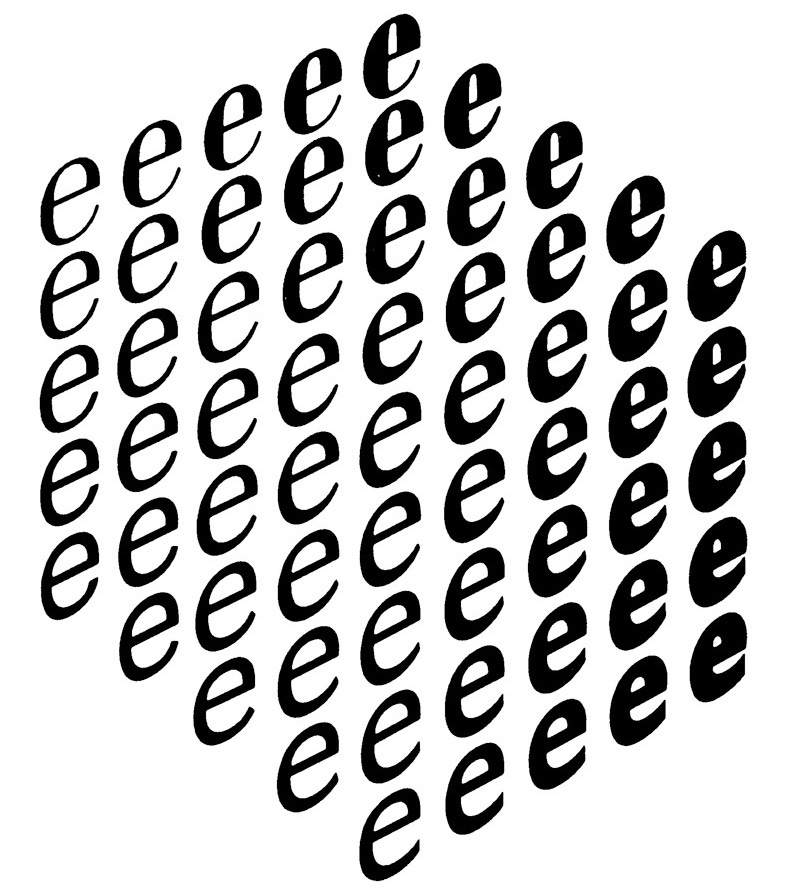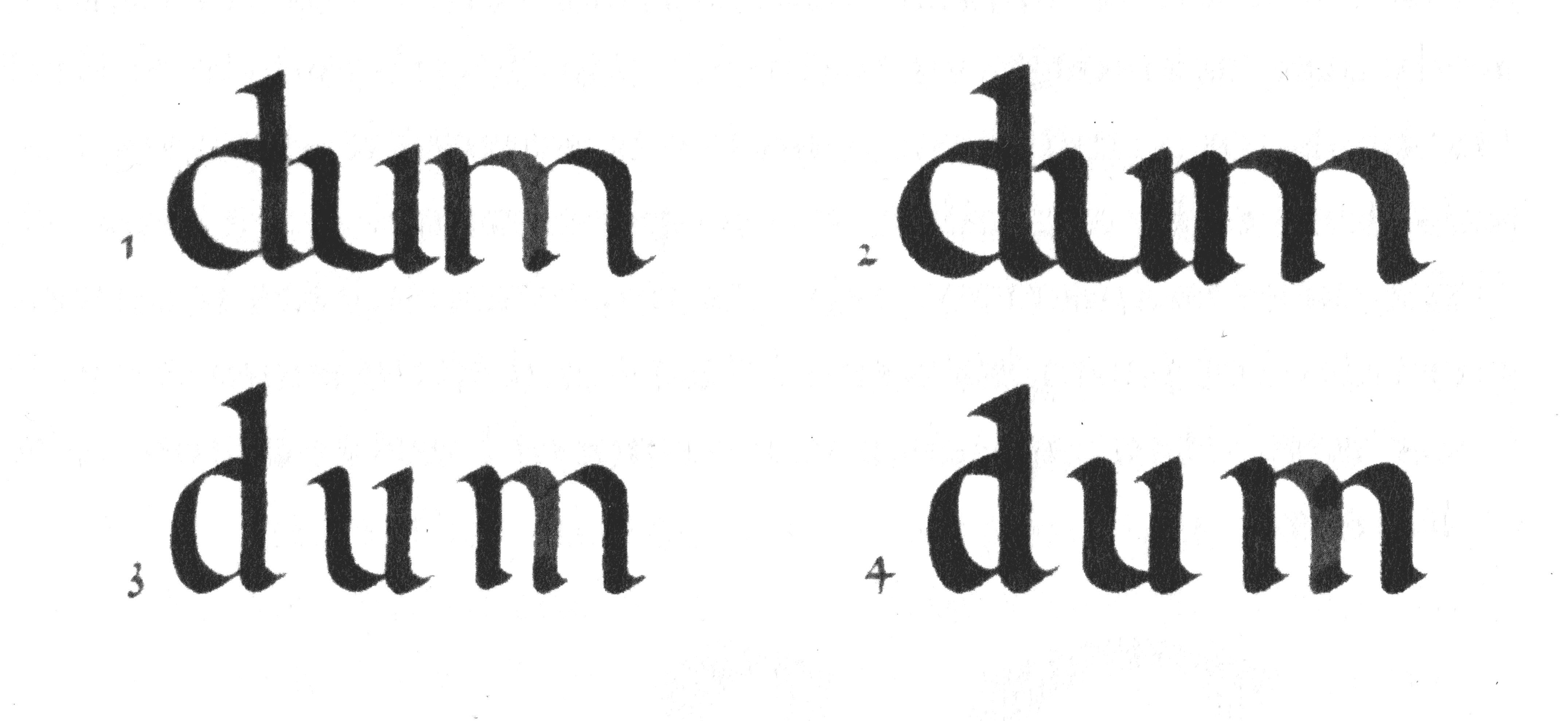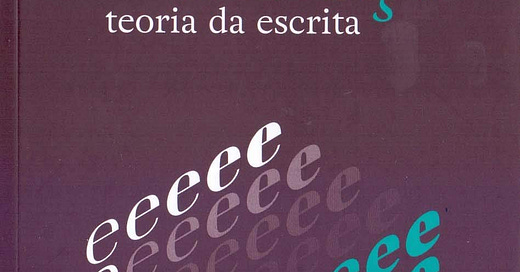
O traço é o artefato fundamental. Nada é mais primordial que a forma de um único traço. Não podemos pressupor uma forma desenhando primeiramente seu contorno, porque qualquer desenho (incluindo os contornos) começa com a forma. Contornos são as bordas das formas. Se uma forma não existir, também não haverá um contorno.
Existe algo encantador no ser humano que desperta quando aprendemos e entendemos algo complexo a partir de seus conceitos mais simples e basilares. Imagine você, quando criança, vendo Carl Sagan explicando a quarta dimensão, um conceito tão intangível e complexo, a partir de um quadrado num plano e uma maçã voadora deixando impressões e fazendo sua silhueta aparecer enquanto ela se move numa dimensão inimaginável para um simples quadrado. Muitas áreas de conhecimento têm a oportunidade de conquistar alguém pelo fascínio de entender as coisas pelas suas fundações, quando temos alguém hábil e generoso o suficiente para explicá-las.
Uma dessas pessoas partiu para as estrelas recentemente: o professor, autor e type designer holandês Gerrit Noordzij. Ao longo de 90 anos vividos em função das letras, Gerrit deixou centenas de alunos, uma vasta contribuição para o ensino de tipografia e design de tipos, e um dos livros mais traiçoeiros que alguém pode (se você vive de tipografia, deve) ter na estante. “Traiçoeiro” num bom sentido, antes que pareça uma crítica vazia: ele é bem curto, tem menos de 100 páginas, mas não quer dizer que seja fácil ou de rápida digestão. No entanto, a compreensão sobre tudo que envolve o ato de desenhar letras nunca mais é a mesma depois de tê-lo lido. Espero que você não tenha pensado mal de mim sobre dizer que o livro é “traiçoeiro”: essa edição de hoje não é uma resenha, crítica ou uma análise formal, é só um compilado de divagações para falar bem de O Traço: teoria da escrita (lançado no Brasil pela Editora Blucher), de como os ensinamentos dele são importantes pra mim e pra qualquer um que viva de criar ou trabalhar com letras.
Os estudos contemporâneos sobre a escrita não observam atentamente o branco da palavra, mas o preto da letras. Consequentemente, as considerações se exaurem na exploração de diferenças superficiais. O ponto de vista universal, que permite a comparação entre a escrita manual e a tipografia, não observa o preto da letra. O preto de uma letra tipográfica é tão diferente do preto de uma letra manuscrita que, em um comparativo rigoroso, eles parecem incomensuráveis.
Quando falo de “criar ou trabalhar com letras”, eu tento ser o mais abrangente possível e incluir as turmas da tipografia, caligrafia e lettering como público-alvo desse livro, o norvana que une todas as tribos. O subtítulo “teoria da escrita” faz parecer que o livro é voltado para quem faz letras manualmente, só que a própria definição de Noordzij sobre tipografia — escrever com letras pré-fabricadas — e as primeiras linhas do primeiro capítulo derrubam essa impressão, em que Gerrit começa falando da dualidade entre as formas claras e escuras das letras. “A forma preta não pode ser alterada sem a mudança da forma branca e vice versa”. Ele não trata os espaços brancos como um simples vazio, mas como um componente indissociável da letra e do processo de escrever: “O branco da palavra é minha única ferramenta para manter as letras juntas”. Isso é universal para quem escreve com tipos, com pena ou com lápis e caneta, e muitos memes de tipografia não existiriam se o designer tivesse mais cuidado com o espaçamento.
Para o type designer, Gerrit sustenta desde o início a importância de entender a escrita manual para o estudo e prática da tipografia. Mesmo a fonte mais mecânica e industrial que você conseguir imaginar agora, talvez uma Helvetica ou qualquer das releituras das letras DIN, tem uma herança de escrita manual nelas. Elas aparecem nas diferenças sutis de contraste (diferença entre os traços mais finos e mais espessos das letras), na formação das serifas e direção das esporas (caso você tenha pensado numa fonte com serifas egípcias), no desenho de incisões. Em fontes mais clássicas, como Garamond, Plantin ou Bembo, a natureza caligráfica das letras é descarada. Nas que têm fundação na pena flexível, como Bodoni, Didot ou Baskerville, ela fica mais disfarçada, mas jamais ausente. O livro cita o caso das Romain du Roi, letras projetadas em grids que obedeciam a princípios cartesianos; só que, no fim das contas, o que virou tipo móvel mesmo foi a habilidade caligráfica de Granjan, inspirado nas letras escritas pelo mestre calígrafo Nicolas Jarry quase 50 anos antes. Não vou me alongar nesse ponto porque… bem… aguarde a próxima quinzena. ;)
Eu falo pouco da minha vivência com tipografia por aqui, mas posso dizer que meu encanto com as formas das letras começou a partir da primeira experiência com uma pena quadrada, feita de um talo de bambu achado em frente ao Instituto de Artes da UnB. Ainda tenho essa pena até hoje; escrever com ela é pouco agradável, o bambu não tem um tratamento adequado para segurar tinta por muito tempo, mas foi o suficiente para desenhar as primeiras letras da escrita fundamental de Johnston. Entender que o ângulo da pena quadrada é o que faz a haste direita da letra “A” ser mais espessa que a esquerda abriu minha cabeça irremediavelmente, e desde então, o bicho da tipografia não me largou mais. Demoraria muito tempo até que “O Traço” encontrasse minha vida, mas as coisas que aprendi experimentando com outras penas quadradas melhores e fazendo workshops de caligrafia estavam todas lá.
A tradução do professor Luciano Cardinali contou com a ajuda da mestra calígrafa Andréa Branco (de quem tive a honra de ser aluno por um fim de semana) para adaptação de termos para o português. As versões em língua local, somadas às ilustrações feitas pelo Noordzij espalhadas por todo o livro, ajudam a transmitir sua teoria de forma sucinta. Mais do que isso, ela ajuda o leitor à conectar-se com o pensamento do autor de como o desenvolvimento da escrita a partir da Idade Média é peça importante para entender a civilização ocidental, a partir da “invenção” da palavra. Não que elas não existissem, em seu sentido estrito; até o Império Romano ocidental, a escrita tinha uma função de transcrever discursos e pensamentos. Com o passar do tempo, ela passou a ter uma função documental, criativa e até gráfica; a palavra é consolidada em forma, com espaços ao seu redor, e em função, encapsulando ideias e conceitos que a linguagem fará sua função de ordená-la corretamente.
A palavra é composta de formas, brancas e pretas, as quais constituem uma unidade rítmica. Se o ritmo for fraco, a formação da palavra é pobre; se o ritmo estiver ausente, não há palavra, mesmo se as letras estiverem dispostas sobre o papel na sequência apropriada.
As pessoas próximas de Noordzij comumente apontavam o quanto ele era devoto às coisas que ele fazia, a ponto de abandonar o ensino médio para dedicar-se a criar algo com as próprias mãos. Ao longo do livro, a devoção dele fica evidente em sua defesa da teoria da escrita, contrapondo-a com o entendimento de escrita de outras áreas de conhecimento, como a história e a pedagogia. Estas, segundo o autor, não têm a devida preocupação de olhar para a escrita além das formas pretas, de seu significado; especialmente com a pedagogia, Noordzij apela para que ela dê mais atenção ao ensino da escrita — em oposição ao crescente abandono do ensino de caligrafia no ensino básico — e à compreensão da palavra.
Noordzij também era devoto ao ensino, tendo formado centenas de alunos — alguns celebrados internacionalmente, como Petr van Blokland, Erik van Blokland, Just van Rossum, e Luc de Groot — que apontam como sua maior virtude a busca por uma forma autêntica e inusitada de ensinar design de tipos. Ele não tinha pudor de pedir para cortar com estilete os trabalhos dos alunos, questioná-los sobre o que eles achavam do trabalho feito e experimentar soluções novas a partir das peças de letras cortadas. “O Traço” é uma versão aperfeiçoada de seu primeiro ensaio, “The stroke of the pen”, que já continha muito da forma dele de ensinar desenho de tipos usando a caligrafia como alicerce, e seu modo de ensinar ainda é muito presente no currículo da especialização em Type and Media da Academia Real de Arte em Haia (KABK).
Fora isso, como disse lá no começo, esse texto não é uma resenha, crítica ou resumo; “O Traço” é um livro que eu queria que tivesse chegado mais cedo na minha vida, que fez parte da especialização em tipografia e que deveria estar em mais estantes Brasil afora, e por isso achei que uma forma justa de homenagear Noordzij seria discorrer sobre criação de letras a partir de sua obra mais famosa. Se você vive de criar letras e te convenci a comprar o livro, meu trabalho aqui está pronto.